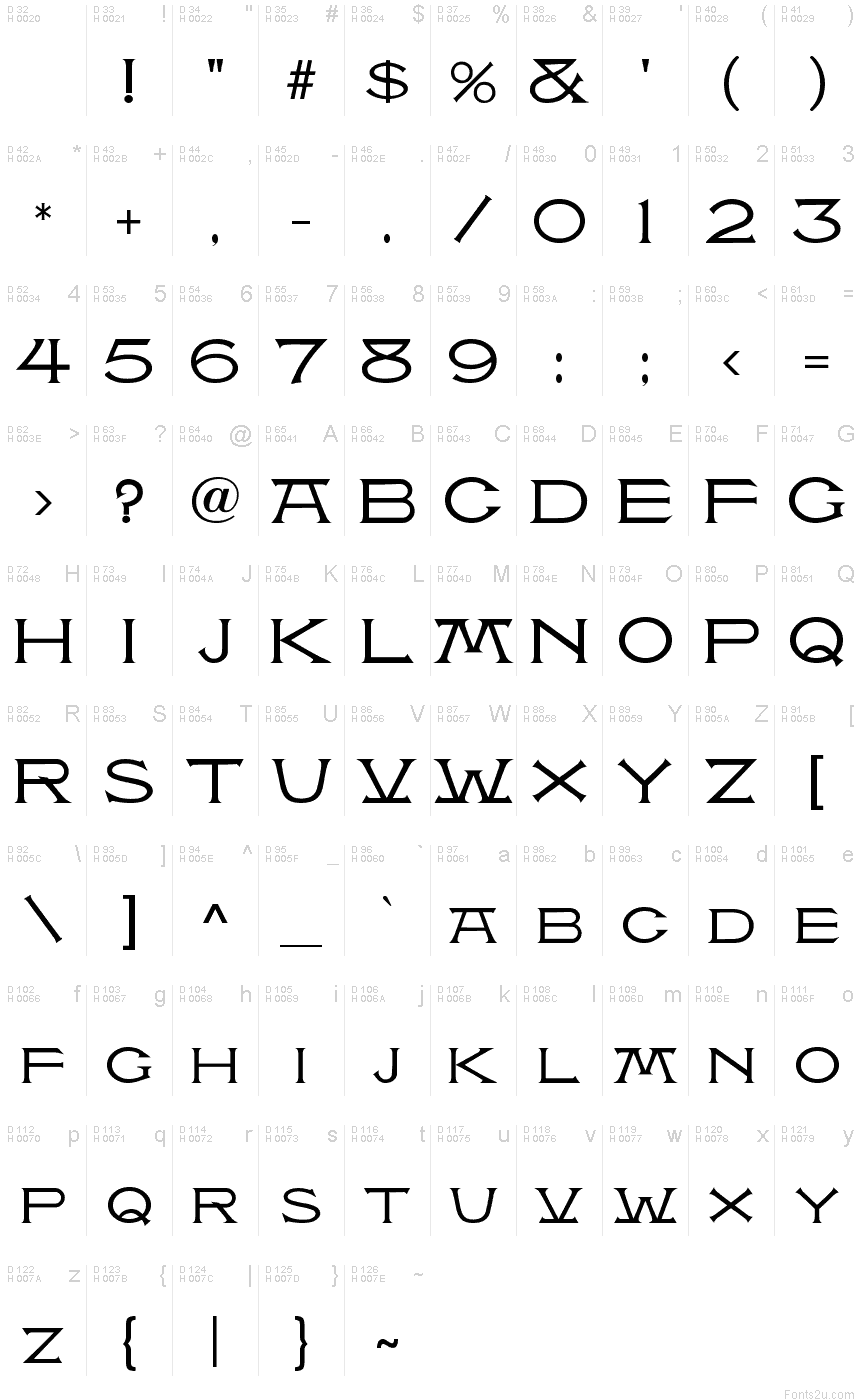
Podgląd czcionki ATLANTIDA
Atlantida autorstwa Cirilicna Slova Dodao Nikola Kovanovic to bezpłatny retro krój typu display o odważnym, inspirowanym stylem Art Déco rytmie. Wielkie litery sprawiają wrażenie wykutych w szerokich, geometrycznych blokach; mieszanka płaskich cięć, kątowych wycięć i trójkątnych otworów nadaje literom wyrazistość plakatów z dawnych lat, zamiast delikatnego, nostalgicznego klimatu.
Idealnie pasuje do brandingu barów, okładek płyt, plakatów imprezowych, opakowań, tytułów oraz krótkich nagłówków, gdzie potrzebujesz bezpłatnego fontu o silnym, zdecydowanym głosie, który nie wygląda przesadnie ozdobnie. Dzięki szerokim, uproszczonym literom i powtarzającym się klinowatym kształtom, ATLANTIDA świetnie sprawdzi się również w monogramach i dużych inicjałach, które wymagają graficznej, niemal architektonicznej obecności.